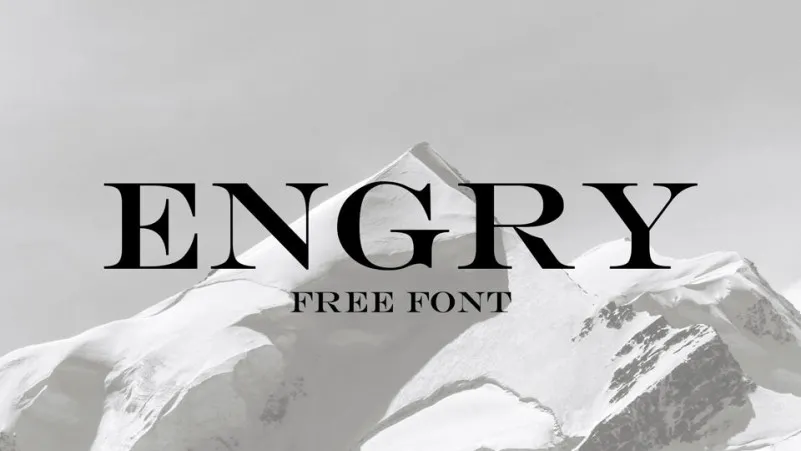
Engry Font – Fonte Grátis
Engry Font
A Engry Font é uma elegante serifada moderna que evolui do estilo de escrita mais antigo de Robert Wiebking, conhecido como Engravers Roman (1899). Esta fonte oferece um amplo leque de letras maiúsculas para uso em capítulos e outros destaque. Ela é perfeita para headlines, moda e vestuário, revistas, cartazes e outros fins de exibição. Possui todas as letras maiúsculas, números e símbolos básicos, suportando tanto a língua latina quanto a cirílica. A Engry Font traz uma dose de sofisticação que se destaca em qualquer aplicação visual. Ideal para profissionais gráficos e designers que buscam um estilo arquitetado em seus projetos.